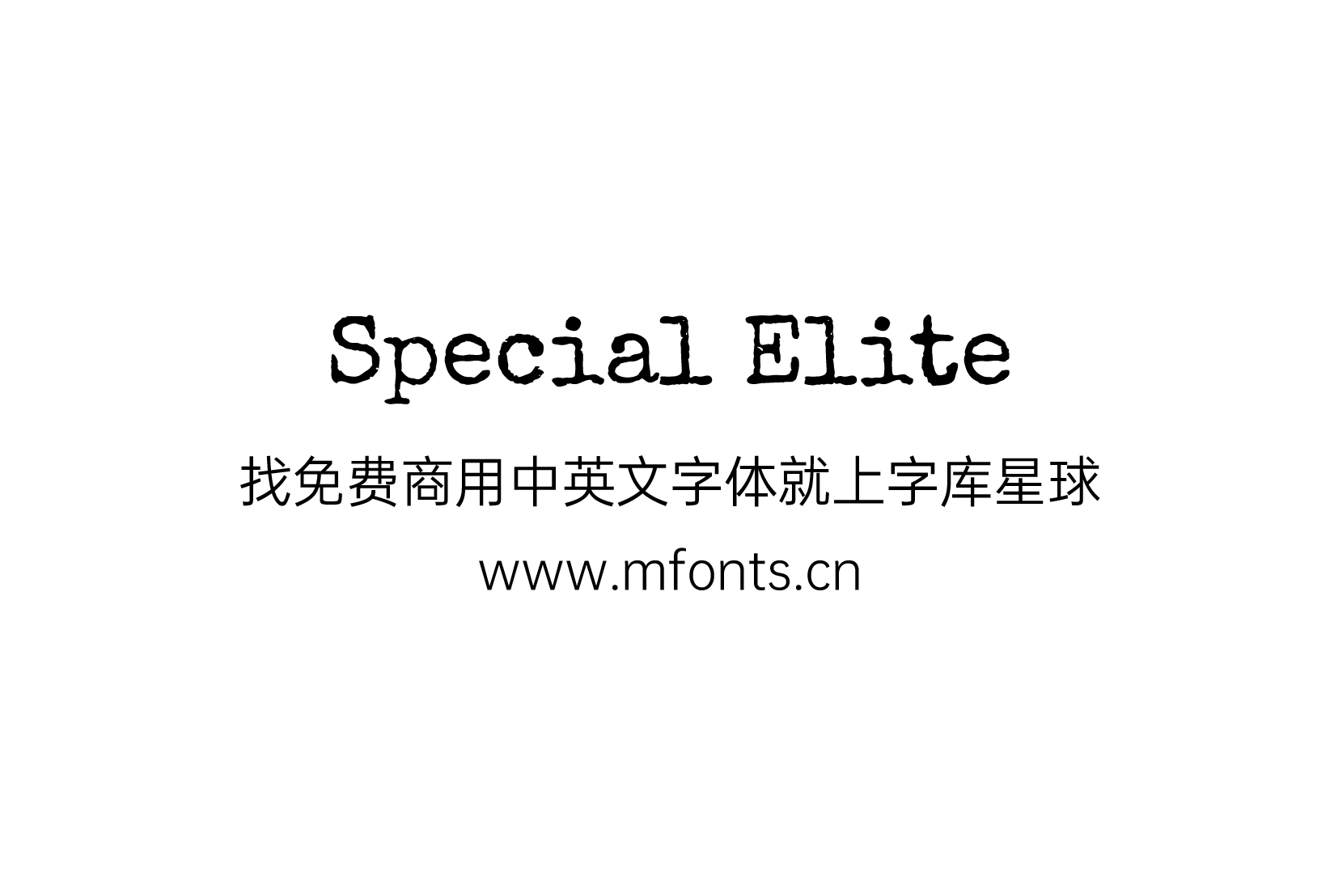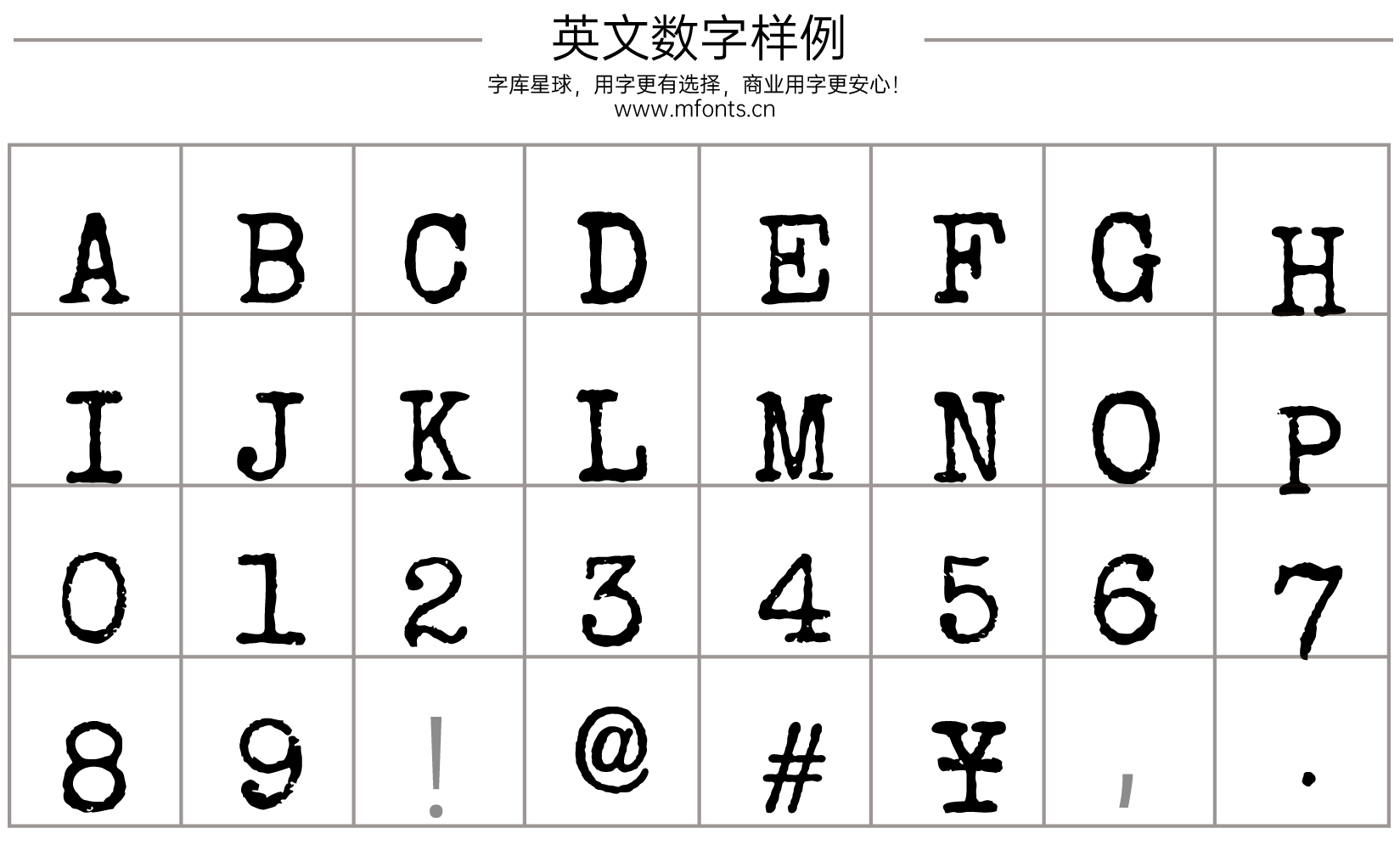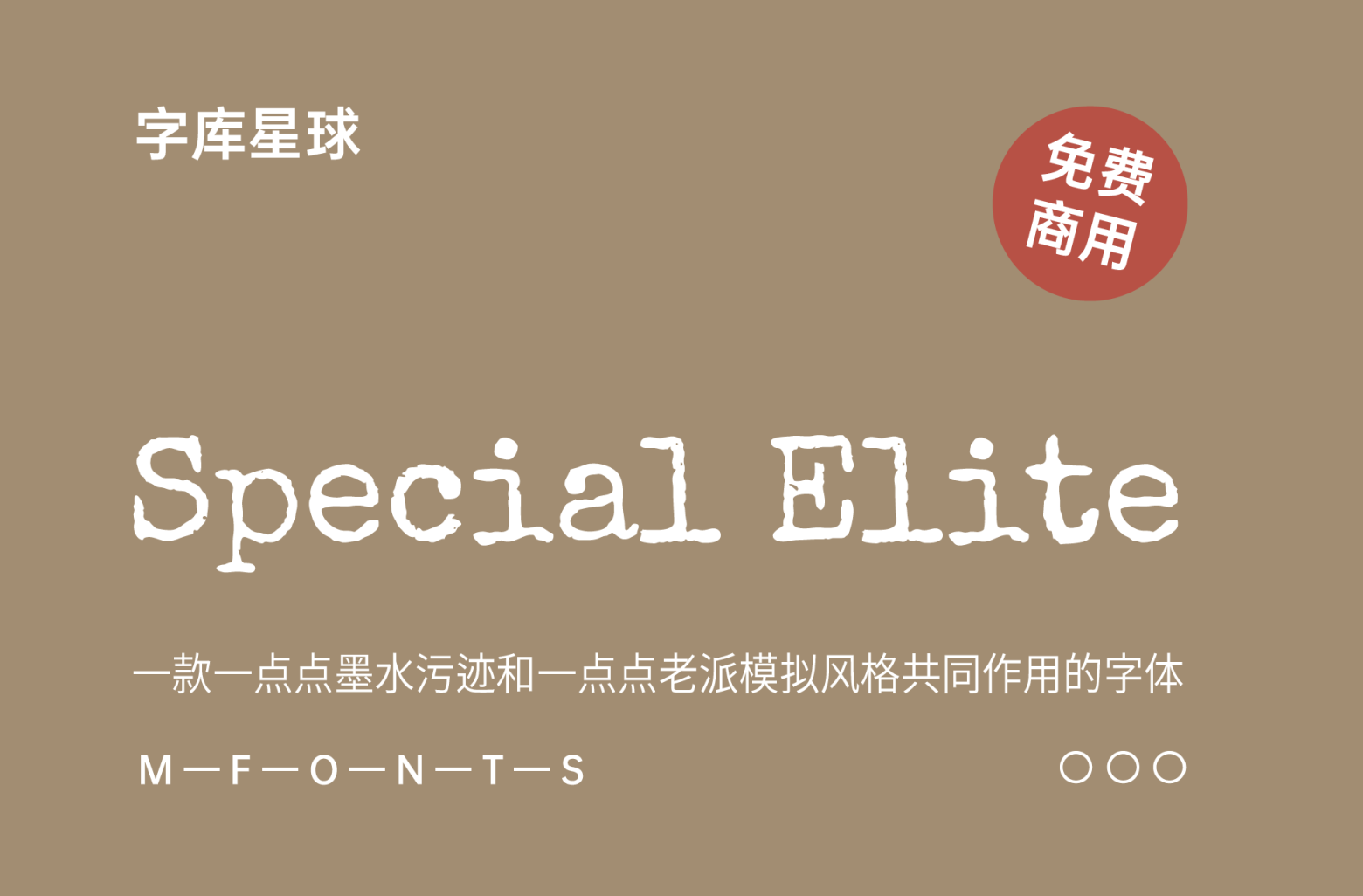
Special Elite
Special Elite是一款模仿了 Smith Corona Special Elite Type Number NR6 和 Remington Noiseless 的免费可商用打字机字体。
一款一点点墨水污迹和一点点老派模拟风格共同作用,为您的网站和设计带来复古打字机字体。